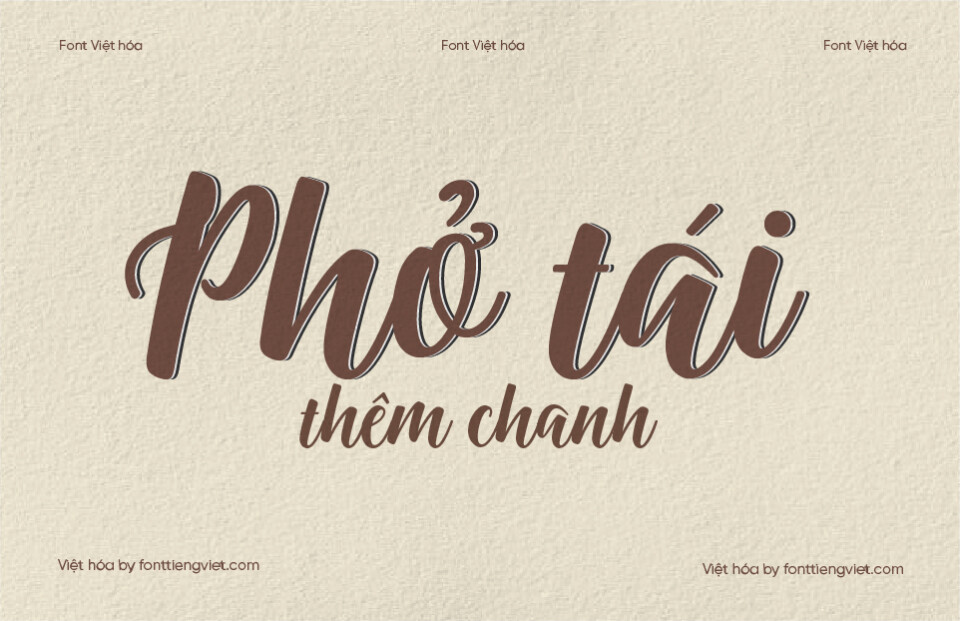
Font Việt hóa 1FTV VIP Onadio – Bộ Font Chữ Sang Trọng Cho Thiết Kế Giáo Dục
Trong thế giới thiết kế đồ họa hiện nay, việc lựa chọn một bộ phông chữ vừa thẩm mỹ vừa hỗ trợ đầy đủ tiếng Việt là điều vô cùng quan trọng. Font Việt hóa 1FTV VIP Onadio nổi lên như một lựa chọn hàng đầu cho các thầy cô giáo và học sinh khi muốn tạo ra những ấn phẩm học đường ấn tượng. Với phong cách thanh lịch và hiện đại, bộ Font Chữ này giúp các bài thuyết trình hay tài liệu học tập trở nên thu hút và chuyên nghiệp hơn bao giờ hết.
Đặc điểm nổi bật của Font Việt hóa 1FTV VIP Onadio
Thiết kế tinh tế và tính ứng dụng cao
Bộ Font Việt hóa 1FTV VIP Onadio sở hữu những đường nét thanh mảnh nhưng vô cùng chắc chắn, mang lại cảm giác dễ chịu cho người xem. Điểm đặc biệt của bộ phông này là khả năng hiển thị tốt trên cả màn hình kỹ thuật số lẫn bản in. Điều này cực kỳ hữu ích cho việc thiết kế giáo án điện tử, làm báo tường hoặc tạo các tấm thiệp chúc mừng trong môi trường nhà trường. Sự chỉn chu trong từng nét chữ giúp nội dung truyền tải trở nên rõ ràng và dễ tiếp thu hơn đối với học sinh.
Hỗ trợ tiếng Việt hoàn hảo cho học tập
Khác với nhiều bộ phông chữ nước ngoài thường bị lỗi dấu khi gõ tiếng Việt, Font Việt hóa 1FTV VIP Onadio đã được tối ưu hóa hoàn toàn. Người dùng có thể yên tâm sử dụng mọi ký tự đặc biệt và dấu câu mà không lo ngại về vấn đề hiển thị. Đây là một công cụ đắc lực giúp các bạn học sinh rèn luyện tư duy thẩm mỹ ngay từ khi ngồi trên ghế nhà trường thông qua các dự án học tập sáng tạo.
Cách sử dụng hiệu quả Font Việt hóa 1FTV VIP Onadio